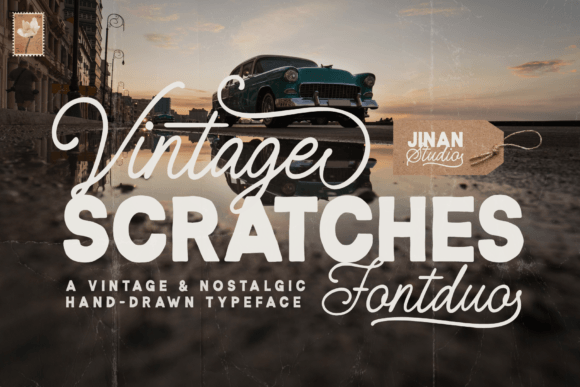
Vintage Scratches Duo
適切なデザイン要素を見つけるのは難しい場合がありますが、Vintage Scratches Duoは作品を即座に引き立てる優れたコレクションを提供します。
POD(オンデマンド印刷)製品、結婚式の招待状、またはソーシャルメディアのグラフィックを作成している場合でも、Vintage Scratches Duoは理想的です。